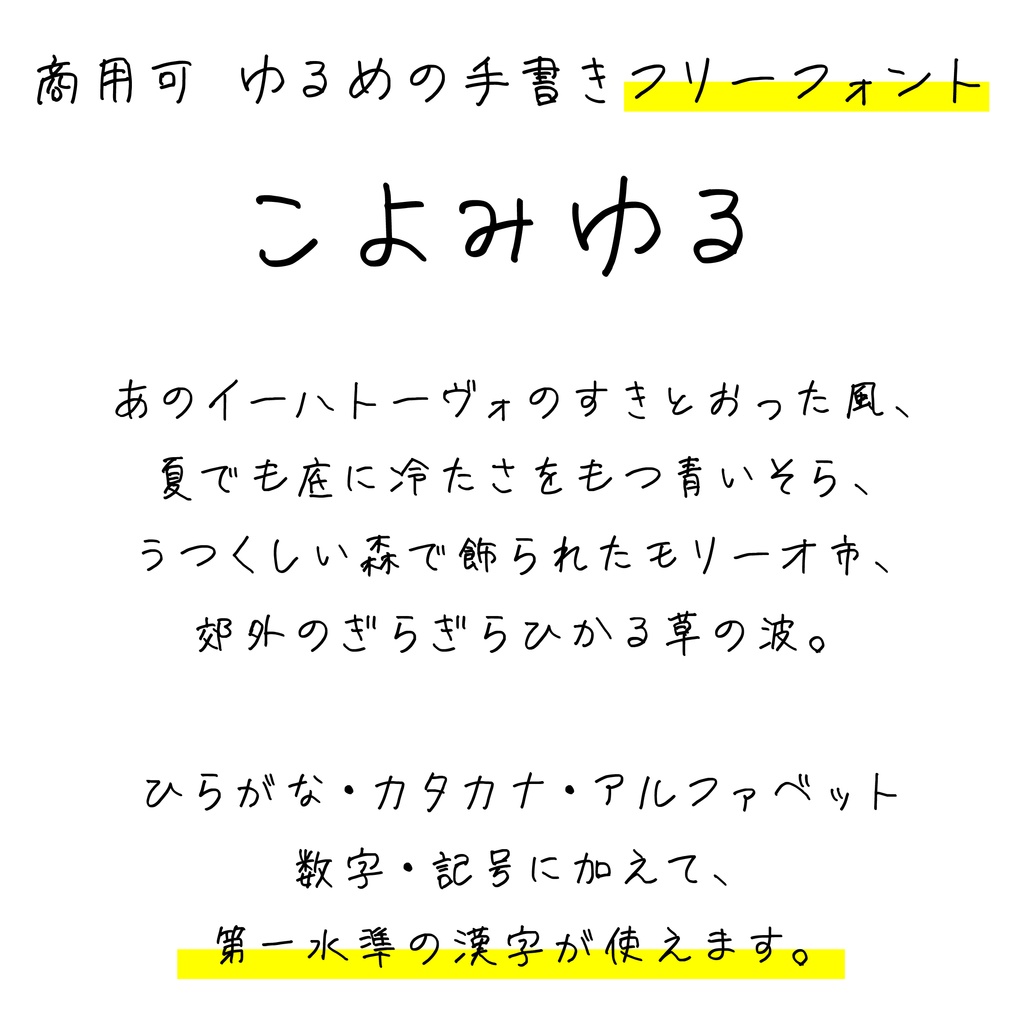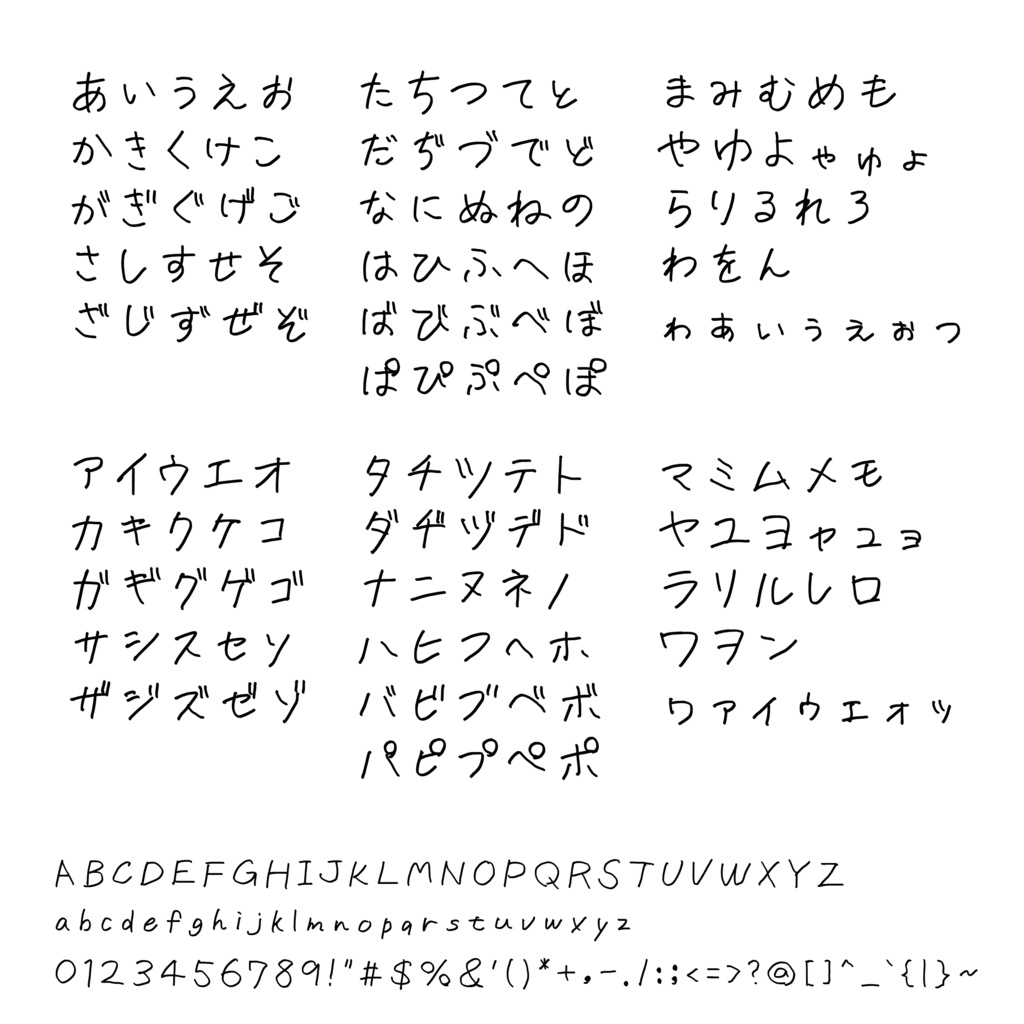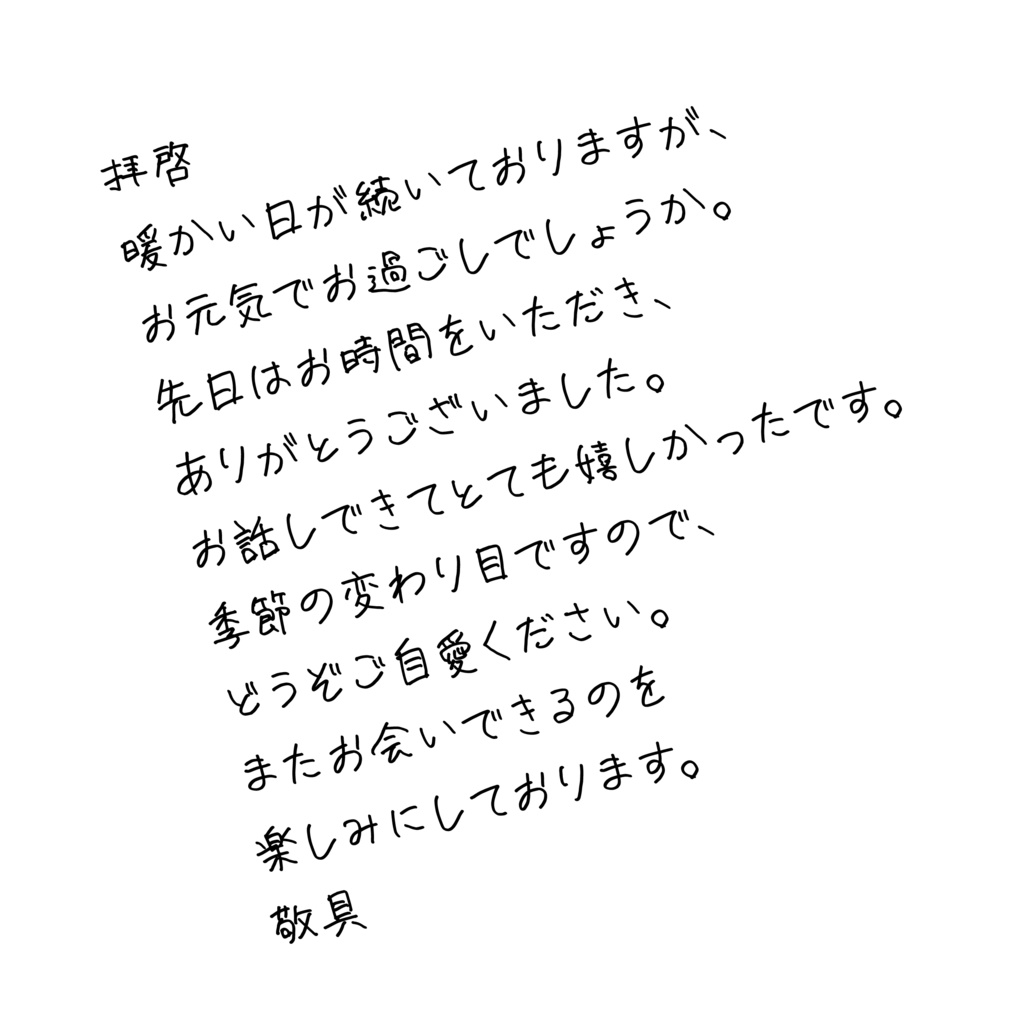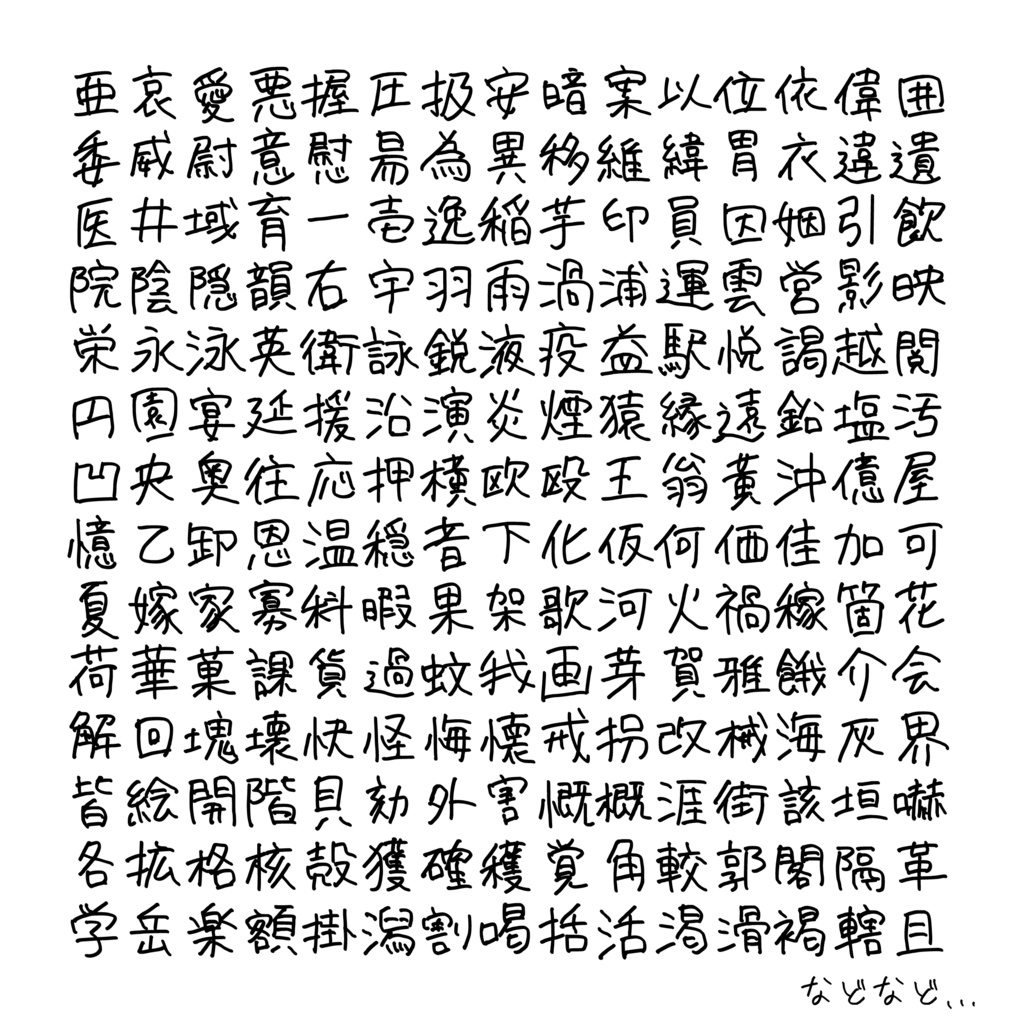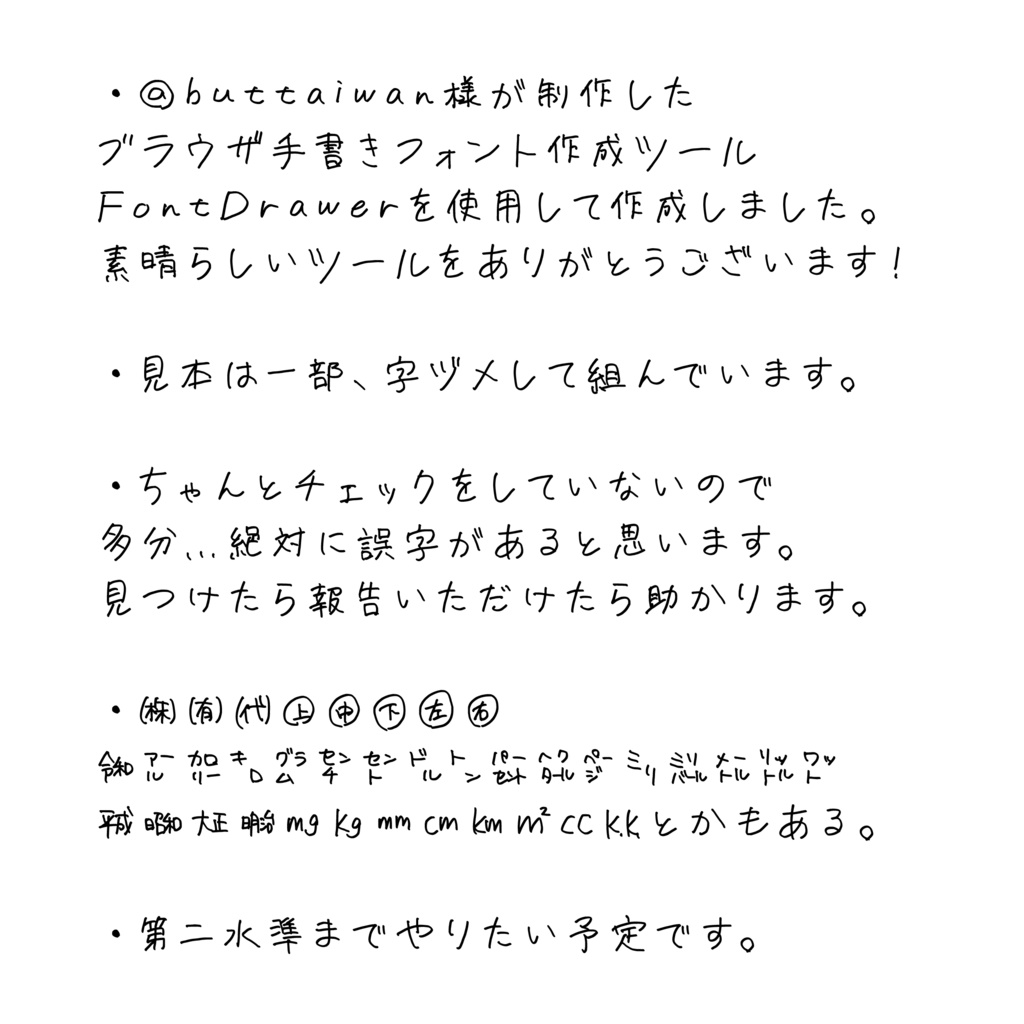
【フリーフォント】こよみゆる【無料・商用利用可】
フリーフォント 「こよみゆる」 こよみゆるはゆるめの手書きフォントです。 ちゃんとチェックをしていないので多分…絶対に誤字があると思います。見つけたら報告いただけたら助かります。 ゆるめに使ってみてください。 ---------------------- SIL Open Font License 1.1 のもとで無償で公開します。 ---------------------- 可能 ・商用利用可能です。 印刷物、web、映像、アプリ、ゲーム(組み込み・埋め込み可能)、同人誌、映像、LINEスタンプ・電子書籍、ロゴなど ・変形、加工可能です。 ・改変、再配布可能です。 ・ロゴなどの商標登録可能です。(加工をおすすめします。) 禁止 ・フォントだけを切り出しての販売はできません。 ---------------------- 収録 ・第一水準漢字(2965字)、ひらがな、カタカナ、数字、アルファベット、約物 ---------------------- ・この規約は予告なく変更する場合がありますが、 有料化やフォントの利用に関して料金を請求するような変更は行いません。 ・著作権は放棄していません。 ・本フォントに起因する故障、損害等に関して当方は一切の責任を負いません。 ・クレジットは不要ですが、記載、ご連絡いただけると制作者が喜びます。 ・@buttaiwan様が制作したブラウザ手書きフォント作成ツール FontDrawerを使用して作成しました。素晴らしいツールをありがとうございます! ・ちゃんとチェックをしていないので多分…絶対に誤字があると思います。見つけたら報告いただけたら助かります。 ・第二水準まで作りたい予定です。 ---------------------- 何かありましたら、BOOTHのメッセージかTwitterの@koyomi_matsubaまでお問い合わせください。 ---------------------- 更新履歴 IKIfont Ver 1.000 2026.04.11 リリース ---- こよみ @koyomi_matsuba ---------------------- 収録文字 !"#$%&'()*+,-.//0123456789:;<=>?@ABCDEFGHIJKLMNOPQRSTUVWXYZ[\]^_`abcdefghijklmnopqrstuvwxyz{|}~§¨°±´¶×÷ΑΒΓΔΕΖΗΘΙΚΛΜΝΞΟΠΡΣΤΥΦΧΨΩαβγδεζηθικλμνξοπρστυφχψωЁАБВГДЕЖЗИЙКЛМНОПРСТУФХЦЧШЩЪЫЬЭЮЯабвгдежзийклмнопрстуфхцчшщъыьэюяё‐―‘’“”†‡‥…‰′″※℃№℡ÅⅠⅡⅢⅣⅤⅥⅦⅧⅨⅩⅰⅱⅲⅳⅴⅵⅶⅷⅸⅹ←↑→↓⇒⇔∀∂∃∇∈∋√∝∞∠∥∧∨∩∪∫∬∴∵∽≒≠≡≦≧≪≫⊂⊃⊆⊇⊥⌒①②③④⑤⑥⑦⑧⑨⑩⑪⑫⑬⑭⑮⑯⑰⑱⑲⑳─━│┃┌┏┐┓└┗┘┛├┝┠┣┤┥┨┫┬┯┰┳┴┷┸┻┼┿╂╋■□▲△▼▽◆◇○◎●◯★☆♀♂♪♭♯、。〃々〆〇〈〉《》「」『』【】〒〓〔〕〜〝〟ぁあぃいぅうぇえぉおかがきぎくぐけげこごさざしじすずせぜそぞただちぢっつづてでとどなにぬねのはばぱひびぴふぶぷへべぺほぼぽまみむめもゃやゅゆょよらりるれろゎわゐゑをん゛゜ゝゞァアィイゥウェエォオカガキギクグケゲコゴサザシジスズセゼソゾタダチヂッツヅテデトドナニヌネノハバパヒビピフブプヘベペホボポマミムメモャヤュユョヨラリルレロヮワヰヱヲンヴヵヶ・ーヽヾ㈱㈲㈹㊤㊥㊦㊧㊨㋿㌃㌍㌔㌘㌢㌣㌦㌧㌫㌶㌻㍉㍊㍍㍑㍗㍻㍼㍽㍾㎎㎏㎜㎝㎞㎡㏄㏍一丁七万丈三上下不与丐丑且丕世丗丘丙丞両並个丫中丱串丶丸丹主丼丿乂乃久之乍乎乏乕乖乗乘乙九乞也乢乱乳乾亀亂亅了予争亊事二于云互五井亘亙些亜亡交亥亦亨享京亭亮人什仁仂仄仆仇今介仏仔仕他仗付仙仝代令以仮仰仲件任企伊伍伎伏伐休会伝伯伴伶伸伺似伽佃但位低住佐佑体何佗余作佯佳併佼使侃例侍供依侠価侭侮侯侵侶便係促俄俊俎俗保俞俠信俣修俱俳俵俸俺倉個倍倒倖候借倣値倦倫倭倶倹偉偏停健偲側偵偶偽傀傍傑傘備催傭傲債傷傾僅働像僑僕僚僧僻儀億儒償優儲儿允元兄充兆兇先光克免兎児党兜入全八公六共兵其具典兼内円冊再冒冗写冠冥冨冫冬冴冶冷凄准凋凌凍凝凡処凧凪凱凶凸凹出函刀刃分切刈刊刑列初判別利到制刷券刹刺刻剃剄則削前剖剛剝剣剤剥副剰割創劃劇劉力功加劣助努劫励労効劾勃勅勇勉動勘務勝募勢勤勧勲勺勾勿匁匂包化北匙匝匠匡匪匹区医匿十千升午半卑卒卓協南単博卜占卦卯印危即却卵卸卿厄厘厚原厨厩厭厳去参又叉及友双反収叔取受叙叛叡叢口古句叩只叫召可台叱史右叶号司吃各合吉吊吋同名后吏吐向君吟吠否含吸吹吻吾呂呆呈呉告呑周呪味呼命咋和咲咳咽哀品哉員哨哩哲哺唄唆唇唐唖唯唱唾啄商問啓善喉喋喚喜喝喧喩喪喫喬喰営喻嗅嗣嘆嘉嘗嘘嘩嘱嘲噂噌噛器噴噸噺嚇嚢囚四回因団困囲図固国圃圏園土圧在圭地坂均坊坐坑坤坦坪垂型垢垣埋城埜域埠埴埵執培基埼堀堂堅堆堕堤堪堰報場堵堺塀塁塊塑塔塗塘塙塚塞塡塩填塵塾境墓増墜墨墳墾壁壇壊壌壕士壬壮声壱売壷変夏夕外夙多夜夢大天太夫央失夷奄奇奈奉奏契奔套奥奨奪奮女奴好如妃妄妊妓妖妙妥妨妬妹妻妾姉始姐姑姓委姥姦姪姫姶姻姿威娃娘娠娩娯娼婁婆婚婦婿媒媛嫁嫉嫌嫡嬉嬢嬬嬰子孔字存孜孝孟季孤学孫宅宇守安宋完宍宏宕宗官宙定宛宜宝実客宣室宥宮宰害宴宵家容宿寂寄寅密富寒寓寛寝察寡寧審寮寵寸寺対寿封専射将尉尊尋導小少尖尚尤尭就尺尻尼尽尾尿局居屈届屋屍屑展属屠屡層履屯山岐岡岨岩岬岱岳岸峠峡峨峯峰島峻崇崎崖崩嵐嵩嵯嶋嶺巌川州巡巣工左巧巨差己巳巴巷巻巽巾市布帆希帖帝帥師席帯帰帳常帽幅幌幕幡幣干平年幸幹幻幼幽幾庁広庄庇床序底庖店庚府度座庫庭庵庶康庸廃廉廊廓廟廠延廷建廻廼廿弁弄弊式弐弓弔引弗弘弛弟弥弦弧弱張強弼弾彊当彙形彦彩彪彫彬彰影役彼往征径待律後徐徒従得御復循微徳徴徹徽心必忌忍志忘忙応忠快念忽怒怖怜思怠急性怨怪怯恋恐恒恕恢恣恥恨恩恭息恰恵悉悌悔悟悠患悦悩悪悲悶悼情惇惑惚惜惟惣惧惨惰想惹愁愈愉意愚愛感慄慈態慌慎慕慢慣慧慨慮慰慶慾憂憎憐憤憧憩憬憲憶憾懇懐懲懸戊戎成我戒或戚戟戦戯戴戸戻房所扇扉手才打払托扮扱扶批承技抃抄抉把抑抒抓抔投抖抗折抛抜択披抬抱抵抹抻押抽拂担拆拇拈拉拊拌拍拏拐拑拒拓拔拗拘拙招拜拝拠拡括拭拮拯拱拳拵拶拷拾拿持指按挑挙挟挨挫振挺挽挿捉捌捕捗捜捧捨据捲捷捺捻掃授掌排掘掛掠採探接控推掩措掬掲掴掻揃描提揖揚換握揮援揺損搬搭携搾摂摘摩摯摸摺撃撒撚撞撤撫播撮撰撲撹擁操擢擦擬擾支改攻放政故敏救敗教敢散敦敬数整敵敷文斉斌斎斐斑斗料斜斡斤斥斧斬断斯新方於施旅旋族旗既日旦旧旨早旬旭旺昂昆昇昌明昏易昔星映春昧昨昭是昼時晃晋晒晦晩普景晴晶智暁暇暑暖暗暢暦暫暮暴曇曖曙曜曝曰曲曳更書曹曽曾替最月有朋服朔朕朗望朝期木未末本札朱朴机朽杉李杏材村杓杖杜束条杢来杭杯東杵杷松板枇析枕林枚果枝枠枢枯架柁柄柊柏某柑染柔柘柚柱柳柴柵査柾柿栂栃栄栓栖栗校栢株栴核根格栽桁桂桃案桐桑桓桔桜桝桟桧桶梁梅梓梗梢梧梨梯械梱梶梼棄棉棋棒棚棟森棲棺椀椅椋植椎椙椛検椴椿楊楓楕楚楠楢業楯楳極楷楼楽概榊榎榔榛槃構槌槍様槙槻槽樋樗標樟模権横樫樵樹樺樽橋橘機橡橿檀檎櫓櫛櫨欄欝欠次欣欧欲欺欽款歌歎歓止正此武歩歪歯歳歴死殆殉殊残殖殴段殺殻殿毀毅母毎毒比毘毛氏民気水氷永氾汀汁求汎汐汗汚汝江池汰汲決汽沃沈沌沓沖沙没沢沫河沸油治沼沿況泉泊泌法泡波泣泥注泰泳洋洗洛洞津洩洪洲活派流浄浅浜浦浩浪浬浮浴海浸涅消涌涙涛涜涯液涼淀淋淑淘淡淫深淳淵混添清渇済渉渋渓渚減渠渡渥渦温測港湊湖湘湛湧湯湾湿満溌源準溜溝溢溶溺滅滋滑滝滞滴漁漂漆漉漏演漕漠漢漣漫漬漸潅潔潜潟潤潮潰澄澗澱激濁濃濠濡濫濯瀕瀞瀦瀧瀬灘火灯灰灸灼災炉炊炎炭点為烈烏烹焔焚無焦然焼煉煎煙煤照煩煮煽熊熔熟熱燃燈燐燕燥燦燭爆爪爵父爺爽爾片版牌牒牙牛牝牟牡牢牧物牲特牽犀犠犬犯状狂狐狗狙狛狩独狭狸狼狽猛猟猪猫献猶猷猿獄獅獣獲玄率玉王玖玩玲珂珊珍珠珪班現球理琉琢琳琴琵琶瑚瑛瑞瑠瑳璃璧環璽瓜瓢瓦瓶甑甘甚甜生産甥用甫田由甲申男町画界畏畑畔留畜畝畠畢略畦番異畳畷畿疋疎疏疑疫疲疹疾病症痔痕痘痛痢痩痴瘍療癌癒癖発登白百的皆皇皐皮皿盃盆盈益盗盛盟監盤目盲直相盾省眉看県真眠眺眼着睡督睦瞥瞬瞭瞳矛矢知矧矩短矯石砂研砕砥砦砧砲破砺砿硝硫硬硯硲碁碇碍碑碓碕碗碧碩確磁磐磨磯礁礎礙示礼社祁祇祈祉祐祖祝神祢祥票祭祷禁禄禅禍禎福禦禰禽禾禿秀私秋科秒秘租秤秦秩称移稀程税稔稗稚稜種稲稼稽稿穀穂穆積穎穏穐穣穫穴究空穿突窃窄窒窓窟窪窮窯窺竃立竜竟章竣童竪端競竹竺竿笈笑笛笠笥符第笹筆筈等筋筏筑筒答策箆箇箋箔箕算管箪箭箱箸節範篇築篠篤篭簡簸簾簿籍籠米籾粁粂粉粋粍粒粕粗粘粛粟粥粧精糊糎糖糞糟糠糧糸系糾紀約紅紋納紐純紗紘紙級紛素紡索紫紬累細紳紹紺終絃組経結絞絡絢給統絵絶絹継続綜綬維綱網綴綻綾綿緊緋総緑緒線締編緩緬緯練緻縁縄縛縞縦縫縮績繁繊繋繍織繕繭繰纂纏缶罣罪罫置罰署罵罷羅羊美羞群羨義羯羽翁翌習翠翫翰翻翼耀老考者而耐耕耗耨耳耶耽聖聞聡聯聴職聾肇肉肋肌肖肘肚肛肝股肢肥肩肪肯肱育肴肺胃胆背胎胞胡胤胴胸能脂脅脆脇脈脊脚脱脳脹腎腐腔腕腫腰腸腹腺腿膏膚膜膝膨膳膿臆臓臣臥臨自臭至致臼興舌舎舗舘舛舜舞舟航般舵舶舷船艇艦艮良色艶芋芙芝芥芦芭芯花芳芸芹芽苅苑苓苔苗苛若苦苧苫英茂茄茅茎茜茨茶茸草荊荏荒荘荷荻莞莫莱菅菊菌菓菖菜菟菩華菰菱萄萌萎萩萱落葉葎著葛葡董葦葬葱葵葺蒋蒐蒔蒙蒜蒲蒸蒼蓄蓉蓋蓑蓬蓮蔀蔑蔓蔚蔦蔭蔵蔽蕃蕉蕊蕎蕗蕨蕩蕪薄薗薙薦薩薪薫薬薮薯藁藍藐藤藩藷藻蘇蘊蘭虎虐虚虜虞虫虹虻蚊蚕蚤蛇蛋蛍蛎蛙蛤蛭蛮蛸蛾蜂蜘蜜蝉蝋蝕蝦蝶蝿融螺蟹蟻血衆行術街衛衝衡衣表衰衷衿袈袋袖被袴袷裁裂装裏裕補裟裡裳裸製裾複褐褒襖襟襲西要覆覇見規視覗覚覧親観角解触言訂訃計訊討訓託記訟訣訪設許訳訴訶診註証詐詑詔評詞詠詣試詩詫詮詰話該詳誇誉誌認誓誕誘語誠誤説読誰課誹誼調談請諌諏諒論諜諦諧諭諮諸諺諾謀謁謂謄謎謙講謝謡謬謹識譜警議譲護讃讐谷豆豊豚象豪豹貌貝貞負財貢貧貨販貪貫責貯貰貴買貸費貼貿賀賂賃賄資賊賎賑賓賛賜賞賠賢賦質賭購贈贋赤赦赫走赴起超越趣趨足距跡跨路跳践踊踏踪蹄蹟蹴躍身躯車軌軍軒軟転軸軽較載輔輝輩輪輯輸輿轄轍轟轡辛辞辣辰辱農辺辻込辿迂迄迅迎近返迦迩迫迭述迷追退送逃逆透逐逓途逗這通逝速造逢連逮週進逸逼遁遂遅遇遊運遍過道達違遜遠遡遣遥適遭遮遵遷選遺遼避還邑那邦邪邸郁郊郎郡部郭郵郷都鄭酉酋酌配酎酒酔酢酪酬酵酷酸醇醍醐醒醗醜醤醸釆采釈里重野量金釘釜針釣釦釧鈍鈎鈴鈷鉄鉛鉢鉦鉱鉾銀銃銅銑銘銚銭鋒鋤鋪鋭鋲鋳鋸鋼錆錐錘錠錦錨錫錬錮錯録鍋鍍鍔鍛鍬鍵鍾鎌鎖鎗鎚鎧鎮鏑鏡鐘鐙鐸鑑鑓長門閃閉開閏閑間関閣閤閥閲闇闘阜阪防阻阿陀附降限陛院陣除陥陪陰陳陵陶陸険陽隅隆隈隊階随隔隙際障隠隣隷隻隼雀雁雄雅集雇雌雑雛離難雨雪雫雰雲零雷電需震霊霜霞霧露青靖静非面革靭靴鞄鞍鞘鞠鞭韓韮音韻響頁頂頃項順須預頑頒頓頗領頚頬頭頰頴頻頼題額顎顔顕願顛類顧風飛食飢飯飲飴飼飽飾餅養餌餐餓館饗首香馨馬馳馴駁駄駅駆駈駐駒駕駿騎騒験騨騰驚骨骸髄高髪髭鬱鬼魁魂魅魔魚魯鮎鮒鮪鮫鮭鮮鯉鯖鯛鯨鯵鰍鰐鰭鰯鰹鰻鱈鱒鱗鳥鳩鳳鳴鳶鴇鴎鴛鴨鴫鴬鴻鵜鵠鵡鵬鶏鶴鷲鷹鷺鹸鹿麓麗麟麦麹麺麻麿黄黍黒黙黛鼎鼓鼠鼻齢龍!()+,-./<=>?[\]^_`~。「」、・ヲァィゥェォャュョッーアイウエオカキクケコサシスセソタチツテトナニヌネノハヒフヘホマミムメモヤユヨラリルレロワン゙゚¢£¬ ̄¥𠮟#$%&*0123456789:;@ABCDEFGHIJKLMNOPQRSTUVWXYZabcdefghijklmnopqrstuvwxyz{|}